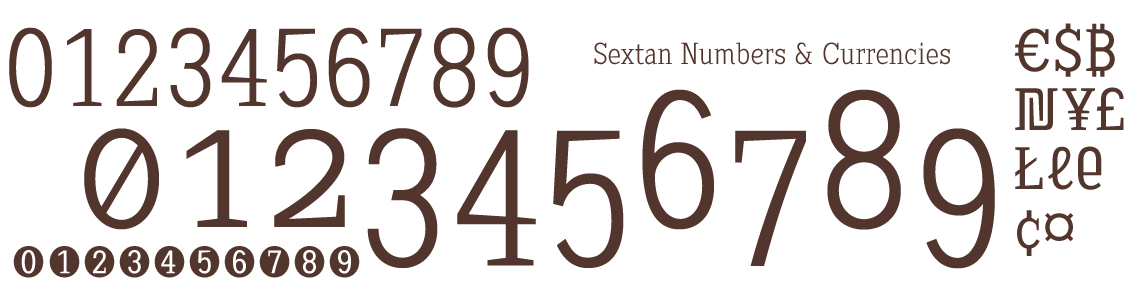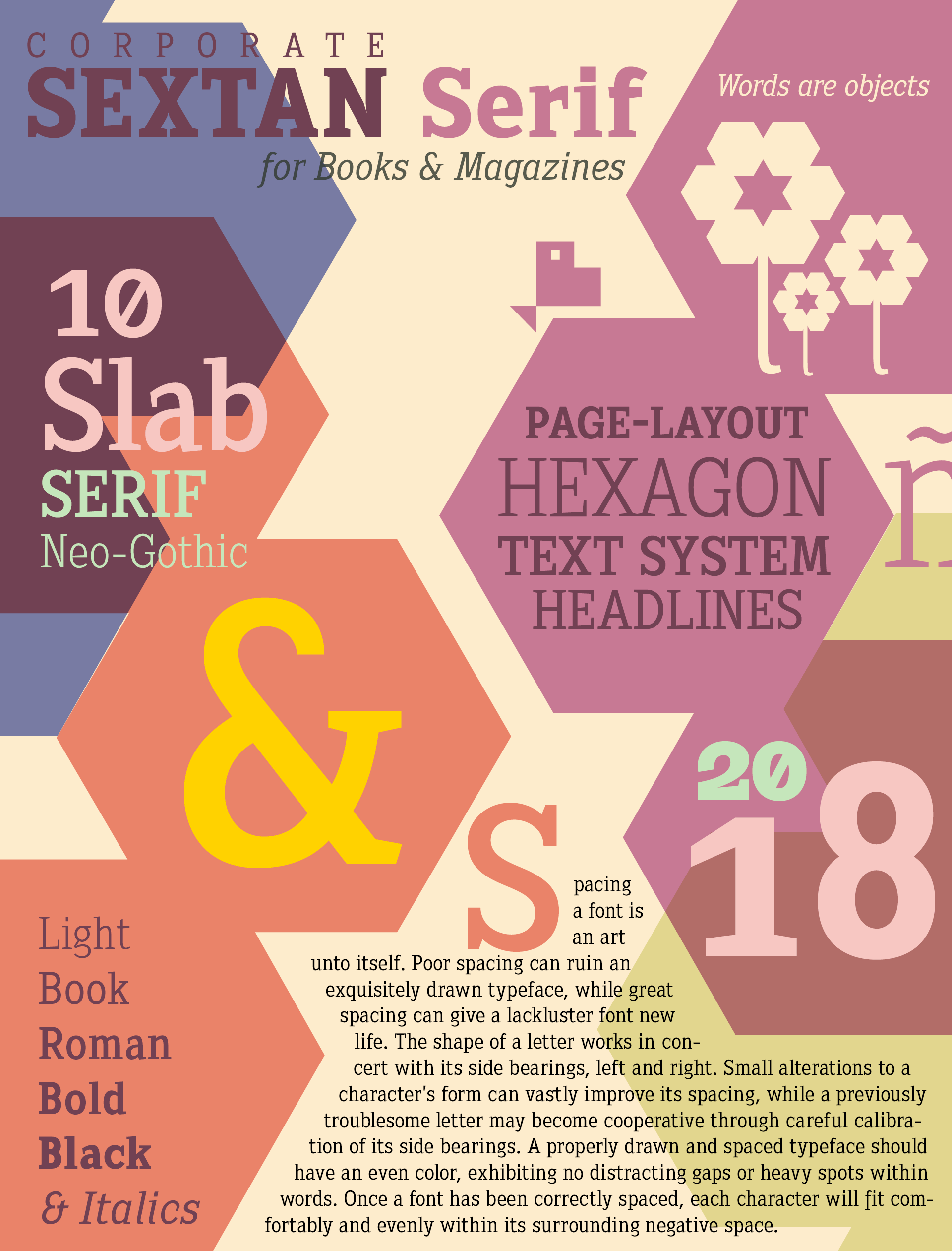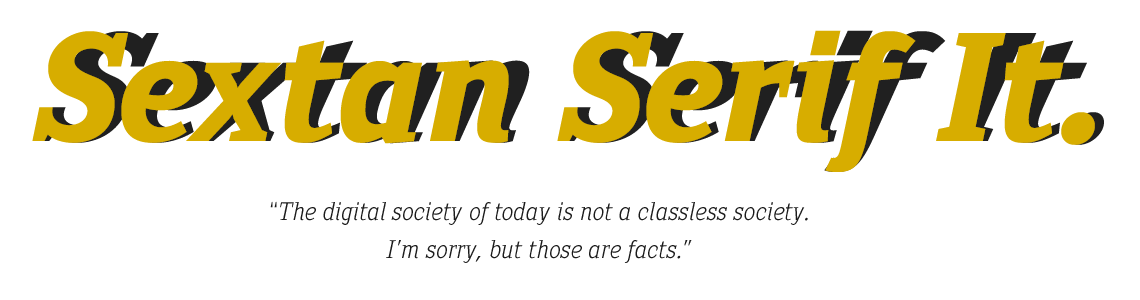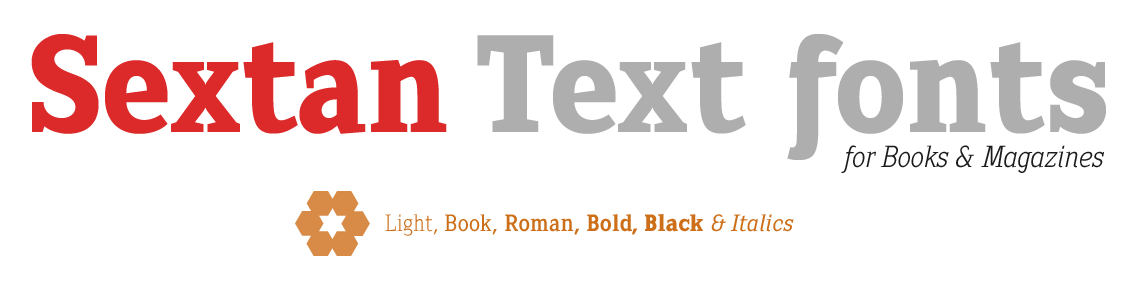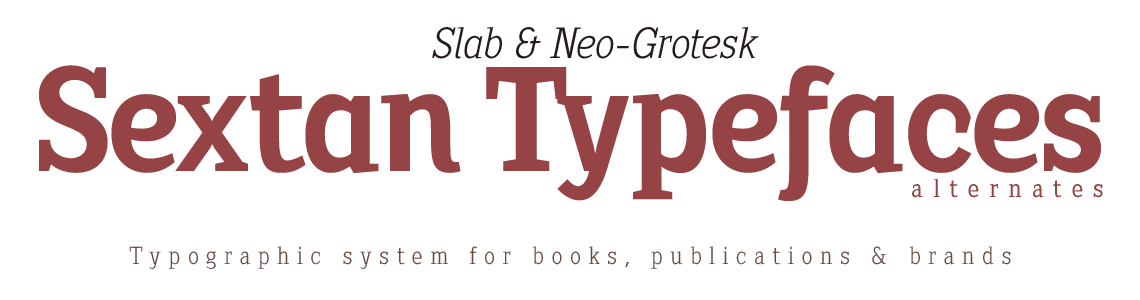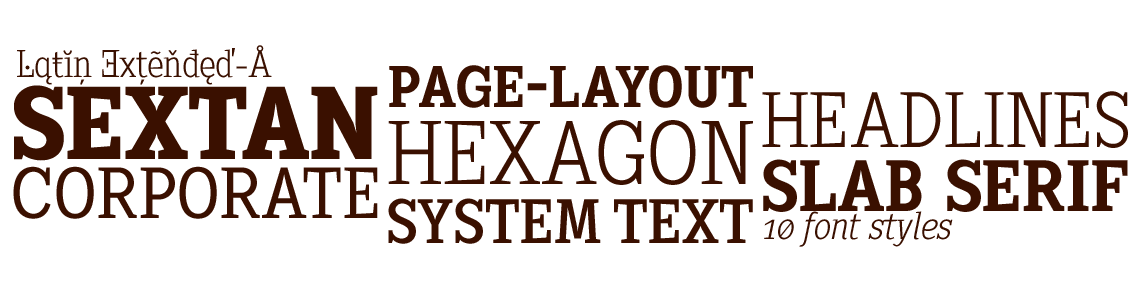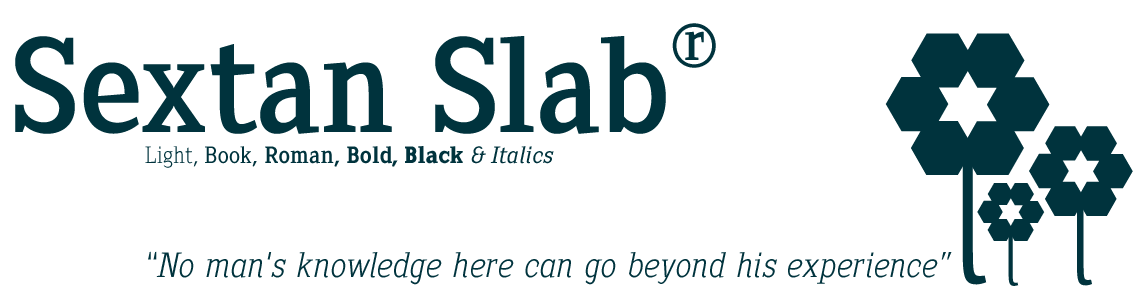
10 Page-Layout Text System Fonts
Estilo: Slab Serif, Neo Grotesca, Corporativa
Proporción: Light, Book, Regular, Bold & Black + Italics
Funciones OpenType: Additional languages, All Alternates, Alternate Annotation Forms, Capital Spacing, Denominators, Discretionary Ligatures, Extended Fractions, Historical Forms, Historical Ligatures, Inferiors, Kerning, Localized Forms, Numerators, Oldstyle Figures, Ordinals, Scientific Inferiors, Slashed Zero, Standard Ligatures, Subscript, Superior letters, Superiors, Superscript.
Latin Extended-A & OpenType Features
Las proporciones de las letras así como las métricas y el kerning se han calculado minuciosamente para obtener la máxima legibilidad en textos de párrafo, los diferentes estilos que incluyen itálicas con minúsculas Ad hoc, ofrecen un sistema tipográfico completo para maquetación de libros, revistas, periódicos o uso en pantalla y Web. Son fuentes muy exclusivas para uso corporativo y diseño publicitario en general.
Las fonts disponen de un juego extra de minúsculas accesibles a través de las Ligaduras Discrecionales. También soporte para Funciones Open Type como Número Old Style, Superiors, Inferiors, Fracciones dinámicas, etc. Incluyen el símbolo del Bitcoin (
b#)
Las fuentes Sextan disponen en su versión comercial de un juego de 533 glifos (Latin Extended-A), con soporte para cualquier idioma europeo o centro europeo. Sextan Serif también incluye funciones OpenType (Compatibles con InDesign, QuarkXpress, Photoshop e Illustrator.